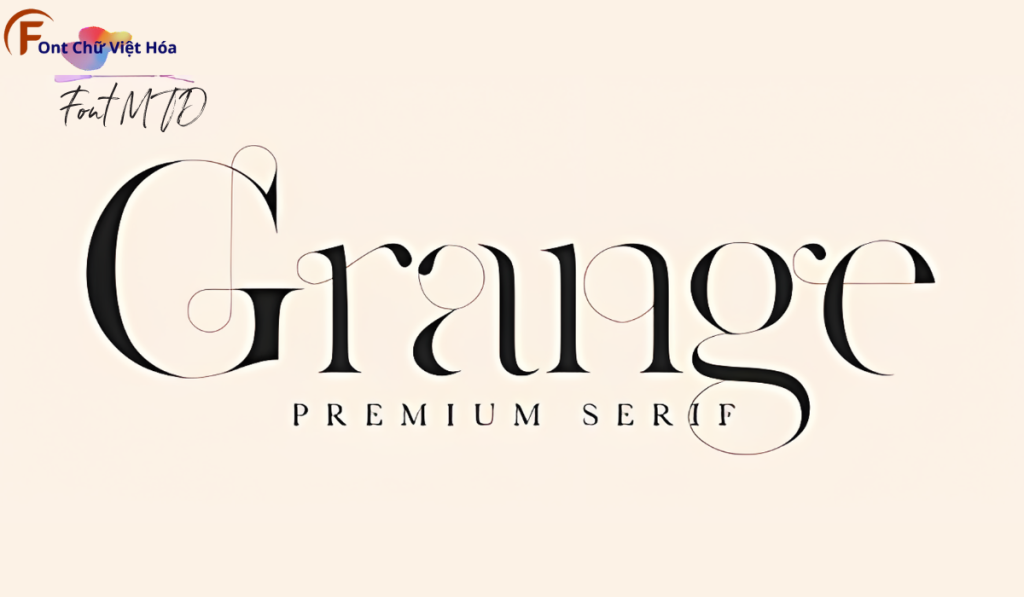
Font MTD Grange C Việt Hóa
Độ dày: Bold, Regular
Font MTD Grange C Việt Hóa, thuộc bộ font MTD, mang phong cách cổ điển và sang trọng, phù hợp cho các dự án thiết kế như thiệp mời, bìa sách, và tài liệu văn phòng. Với các nét chữ có chân và độ dày đa dạng, Font MTD Grange C Việt Hóa không chỉ dễ đọc mà còn tạo cảm giác lịch lãm và chuyên nghiệp. Việc Việt hóa font giúp người dùng dễ dàng tích hợp vào các thiết kế tiếng Việt, mang lại sự tiện lợi và nâng cao tính thẩm mỹ.